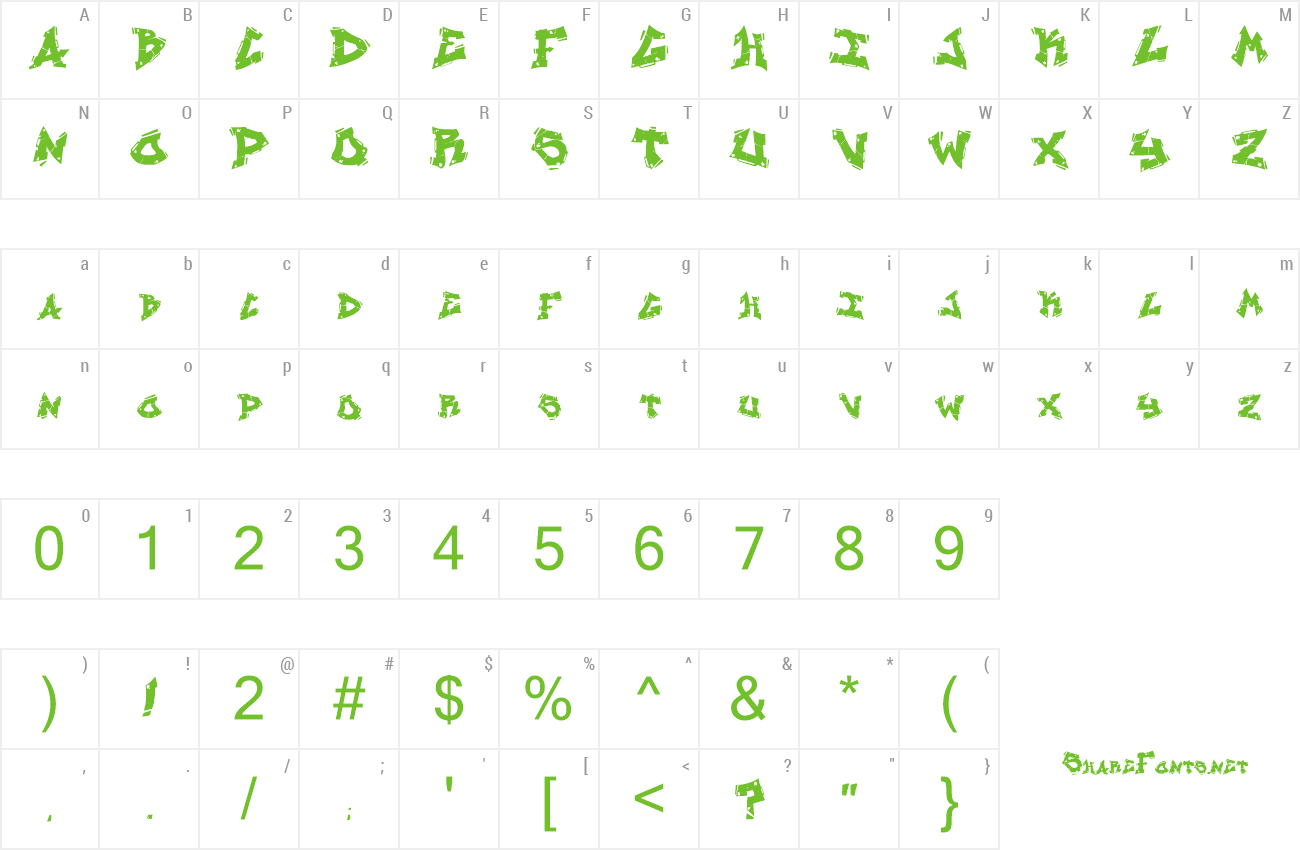
Soacha Letter Font Font
Font name: Soacha Letter Font
Categories Graffiti, Script
Author: JoTa_G
Esta fuente tipogr�fica fue elaborada a partir de el an�lisis de la mayor�a de los grafitis que se encuentran en Soacha-Cundinamarca Colombia. Con el objetivo de generar apropiaci�n por el grafiti Suachuno.